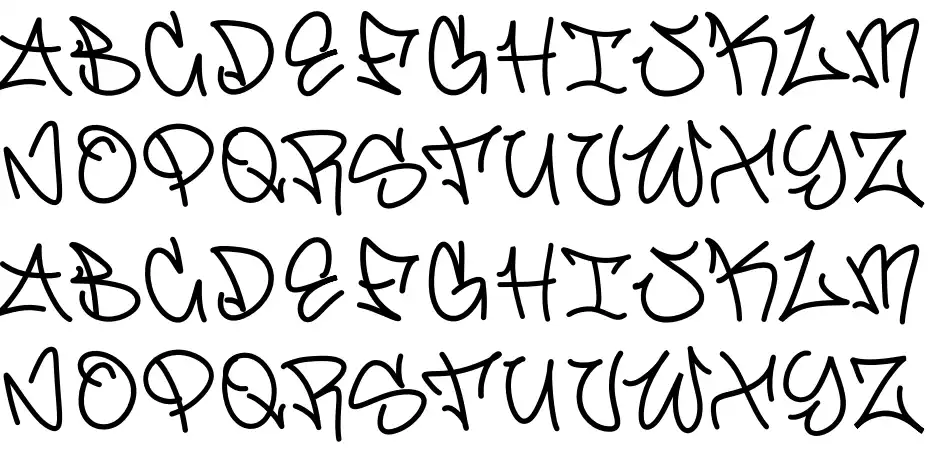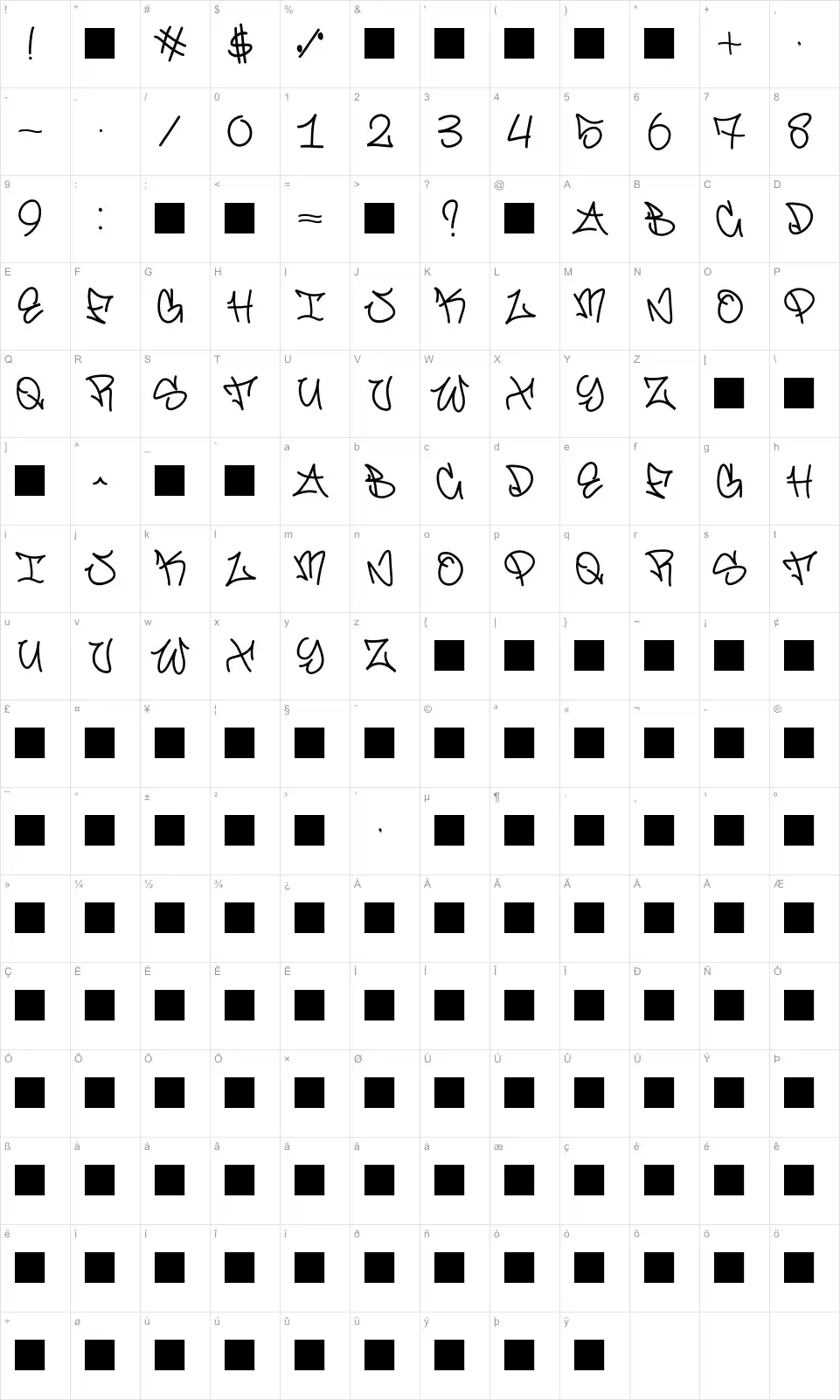
A fonte ‘Graffiti’ foi criada pelo designer Joris Oostinga e é uma opção ideal para quem busca uma fonte moderna e criativa. Se procura uma fonte de escrita casual, com letras suaves e linhas onduladas, esta é a fonte perfeita. Com apenas alguns cliques, você pode usá-la em seu próximo projeto digital. Seja para criar um site moderno, editar fotos ou até mesmo escrever mensagens de texto, a fonte ‘Graffiti’ vai ajudar você a destacar seu trabalho. Com um formato em TTF (True Type Font), é compatível com uma ampla variedade de plataformas e programas de escritório. A fonte aderiu na categoria Script > Graffiti em 12 de julho de 2022, e já foi baixada pelo número impressionante de 4617 usuários. Recomendamos que você faça seu download da fonte ou crie uma prévia personalizada do texto para ver como a fonte se adequa a seu projeto antes de usá-la. Com tamanho de arquivo de 19 KB, ‘Graffiti’ é uma fonte leve e rápida para seu trabalho diário.